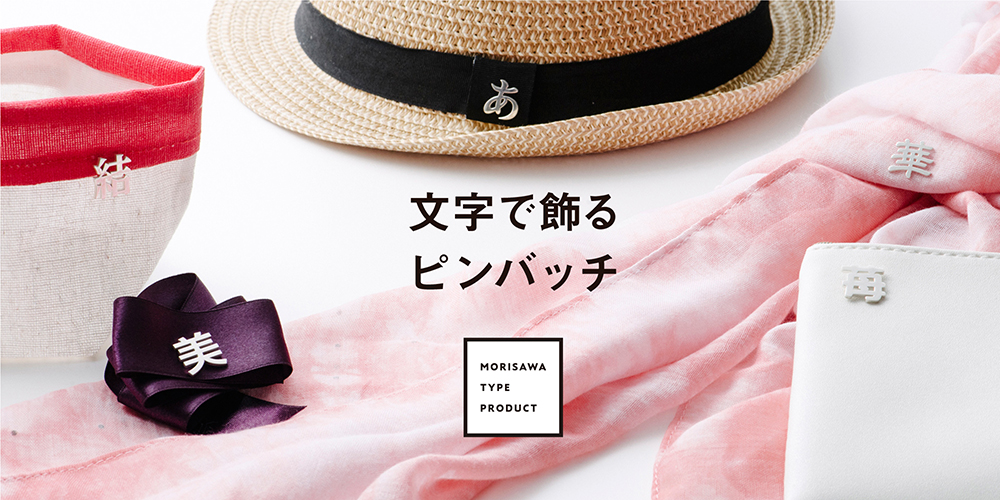
- MORISAWA TYPE PRODUCT第3弾「文字で飾るピンバッチ」
- どん判!?誰が買うのか…アンチックを入れているあたりフォント男子信者のお布施か「文字で飾るピンバッチ」
- 「MORISAWA TYPE PRODUCT」による謎ラインナップ。活字ブックマーカー、手ぬぐい、お香…。そんなグッズより「フォントかるたモリパス版」でも出せば売れそうだ
MORISAWA TYPE PRODUCT第3弾「文字で飾るピンバッチ」
モリサワは、「MORISAWA TYPE PRODUCT」オリジナルグッズの第3弾として「MORISAWA TYPE PRODUCT SHIRO」より銀製の「文字で飾るピンバッチ」を4月10日のフォントの日に発表した。
「MORISAWA TYPE PRODUCT」は、モリサワの書体と日本のものづくりへのこだわりを融合させたオリジナルグッズを制作するプロジェクト。デザインや品質、機能性に優れた日本文化の素晴らしさを世界に発信していく事を目的としている。
「MORISAWA TYPE PRODUCT」は、グッズの個性に応じて「MORISAWA TYPE PRODUCT KURO」と「MORISAWA TYPEPRODUCT SHIRO」の二つのラインナップとして企画し商品化を進めている。
「MORISAWA TYPE PRODUCT SHIRO」では、文字が持つ楽しさ・豊かさをモリサワの多彩な書体に遊び心をプラスした商品ラインナップになっている。
「文字で飾るピンバッチ」は装いのアクセントとなる一文字が上品で美しいシルバー素材のピンバッチとなっており、どんなシーンでも使いやすいデザインで文字の持つイメージと書体のデザインを楽しめる。全5種類のラインナップで、贈り物にもおすすめのアイテム。
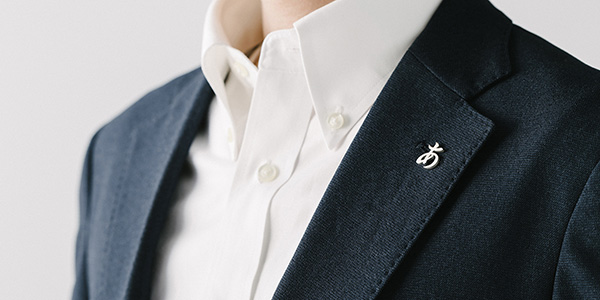
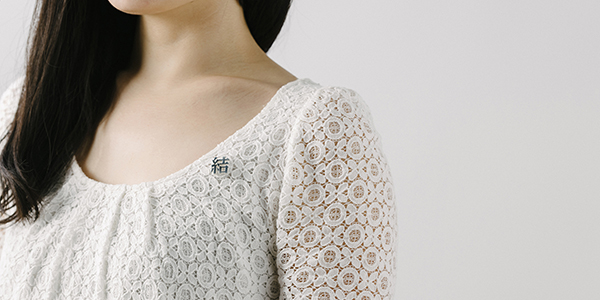
文字で飾るピンバッチ「結」[むすぶ] 黎ミンY40 H
「黎ミン」はシンプルで親しみやすい表情をもつ現代的な明朝体。広めのフトコロをもち、かなの字幅の差が小さいモダンな設計で、くせがなく明快な印象をもつ書体。
文字で飾るピンバッチ「華」[はな] 隷書101
「隷書101」はどっしりとした落ち着きのある隷書体。正方形の骨格を持つため縦組みと横組みのどちらでも使いやすく、全体に力強く、江戸文字に通じる勢いのあるユニークな字形を持っている。
文字で飾るピンバッチ「美」[うつくしい] 新ゴDB
「新ゴ」はシステマチックな雰囲気をもつ現代的なゴシック体。装飾のない均質なデザインで、縦組み、横組みともラインや黒みの揃った、可読性の高い美しい文字組みを実現。
文字で飾るピンバッチ「あ」[あ] アンチックAN2
「アンチック」はゴシック体漢字にあわせた太かなとして、辞書の見出しや絵本、マンガの吹き出しなどに用いられてきた。全体に太みの差が少なく、丸みを帯びた表情が特徴で、安定感と可読性がある。
文字で飾るピンバッチ「苺」[いちご] ソフトゴシック H
「ソフトゴシック」は角の表情に変化をつけた新しい丸ゴシック体。丸ゴシックでは通常「ゲタ」のないデザインが普通だが、これを残していることでひと味ちがったユニークな表情をもっている。
どん判!?誰が買うのか…アンチックを入れているあたりフォント男子信者のお布施か「文字で飾るピンバッチ」
「MORISAWA TYPE PRODUCT」による謎ラインナップ。活字ブックマーカー、手ぬぐい、お香…。そんなグッズより「フォントかるたモリパス版」でも出せば売れそうだ
「文字で飾るピンバッチ」に限らず、「MORISAWA TYPE PRODUCT」のラインナップも謎だ。モリサワフォント、ひいてはフォントの普及を一般層に浸透させる腹積もりからもしれないが、活字ブックマーカー、手ぬぐい、お香…。フォントをメインに押し出して売れるグッズだろうか。
異なる書体で同じ文面が印刷された取り札と書体の名称・解説・見本が印刷された読み札を使用して、かるた取りをするという話題になった「フォントかるた」というかるたがある。このかるたは、もともとモリサワのフォント使用率が高いが、この「フォントかるた」に協力してもらって、MORISAWA PASSPORT(モリサワパスポート)収録のフォントのみを収録した「フォントかるた モリパス版」でも作ってもモリサワストアから出した方がよっぽど売れそうな気がする。定期的にMORISAWA PASSPORTに収録される新書体を追加版としてかるたに継ぎ足していけば、継続して販売できそうでもある。
フォントをメインにグッズ化するなら、モリサワの「UDデジタル教科書体」とは真逆だが読みにくさゆえに覚えやすいフォント「Sans Forgetica」を使用した英単語辞典などが良い。
フォントをメインにグッズ化するなら、モリサワの「UDデジタル教科書体」とは真逆の発送かもしれないが、読みにくさゆえに記憶に定着させやすいという欧文フォント「Sans Forgetica」を使用した英単語辞典などが良いと思う。このフォントは別にモリサワのフォントではないが…。